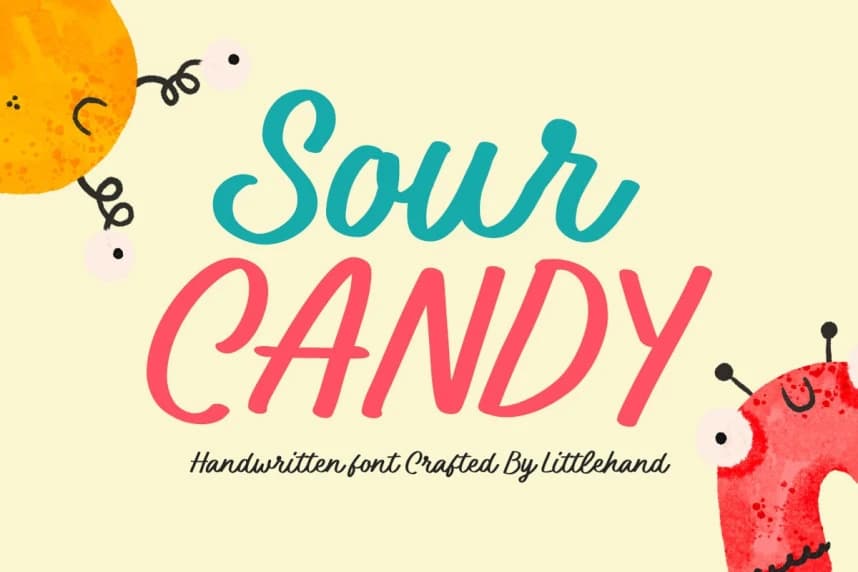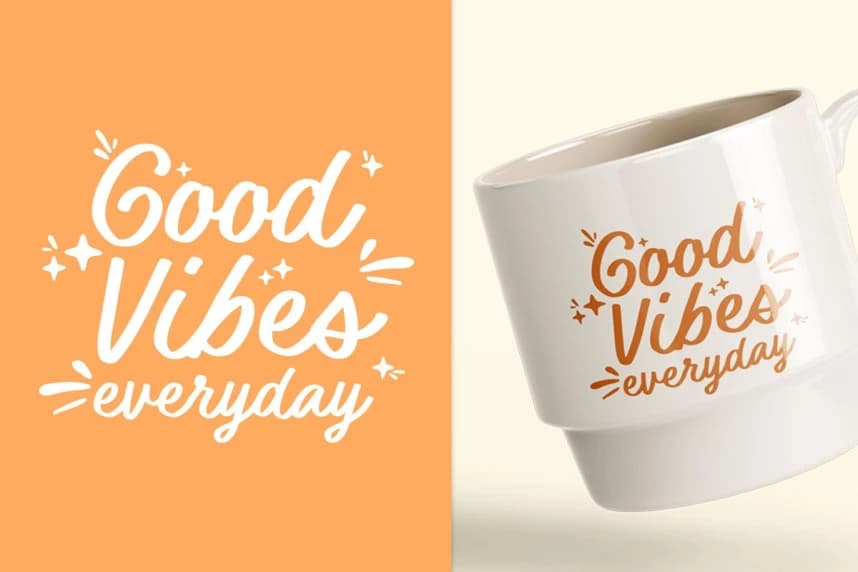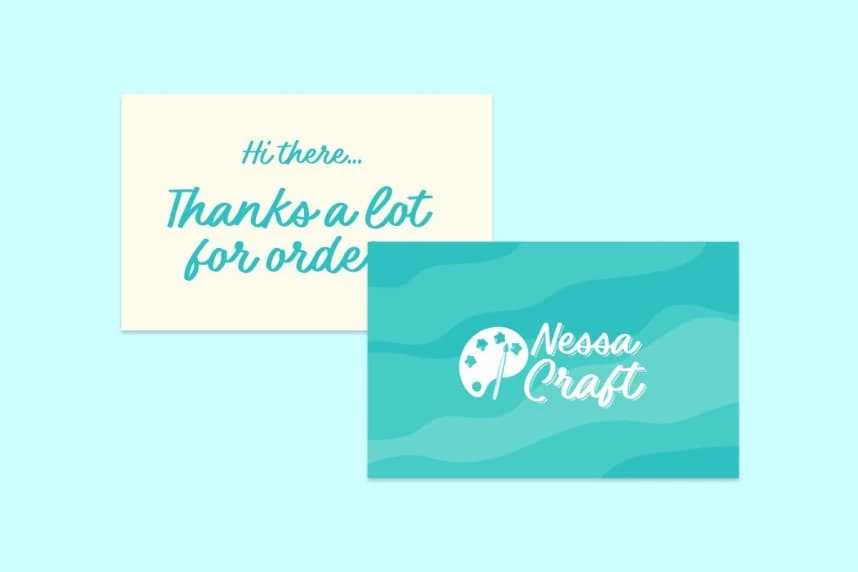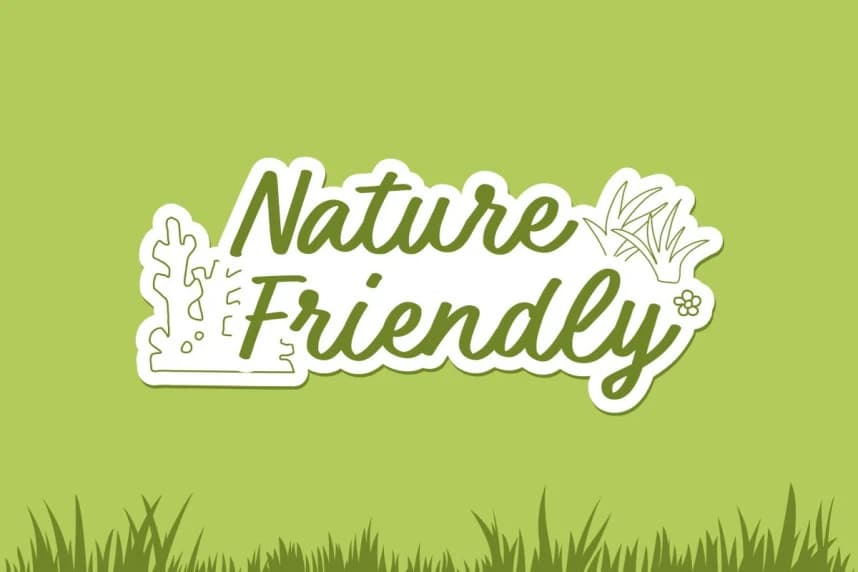
Sour Candy Handwriting Font
Sour Candy Handwriting Font parlak, enerjik ve tatlı bir enerjiyle dolu hissi verir — tipografik olarak hızlı bir şeker yükselmesi gibi. Zıplayan el yazısı çizgileri, akıcı eğrileri ve hafif kalın akışıyla bu font, eğlenceli ve oyuncu bir hava getirir ve anında dikkat çeker.
Sour Candy Handwriting Font parlak, enerjik ve tatlı bir enerji hissi veriyor—tipografik olarak hızlı bir şeker patlamasına benziyor. Zıplayan el yazısı çizgileri, pürüzsüz eğrileri ve hafif kalın akışıyla bu font, anında dikkat çeken eğlenceli ve oyuncu bir hava katıyor.
Sour Candy Handwriting